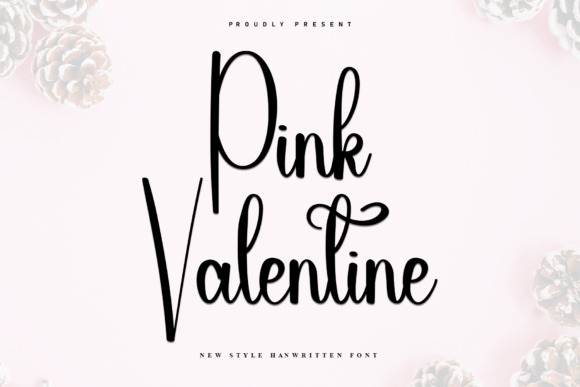
Pink Valentine
適切なデザイン要素を見つけるのは難しい場合がありますが、Pink Valentineは作品を即座に引き立てる優れたコレクションを提供します。
POD(オンデマンド印刷)製品、結婚式の招待状、またはソーシャルメディアのグラフィックを作成している場合でも、Pink Valentineは理想的です。